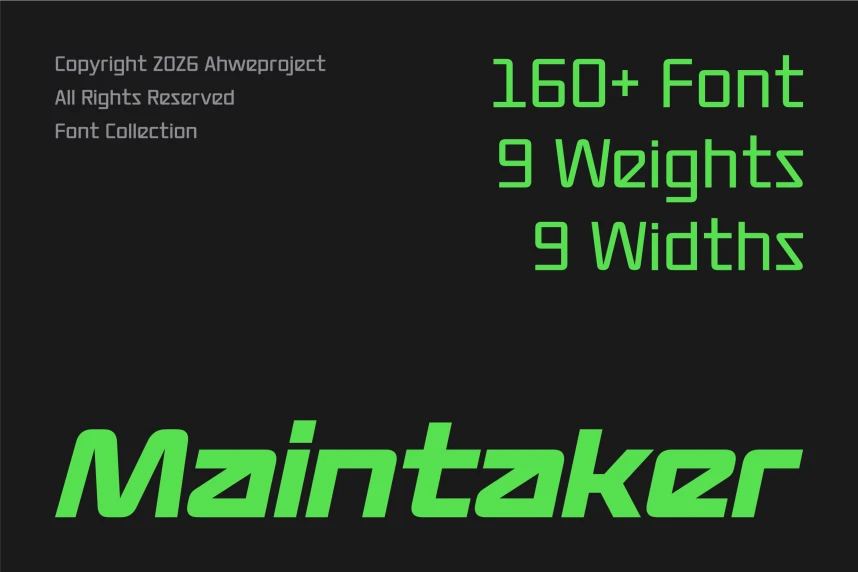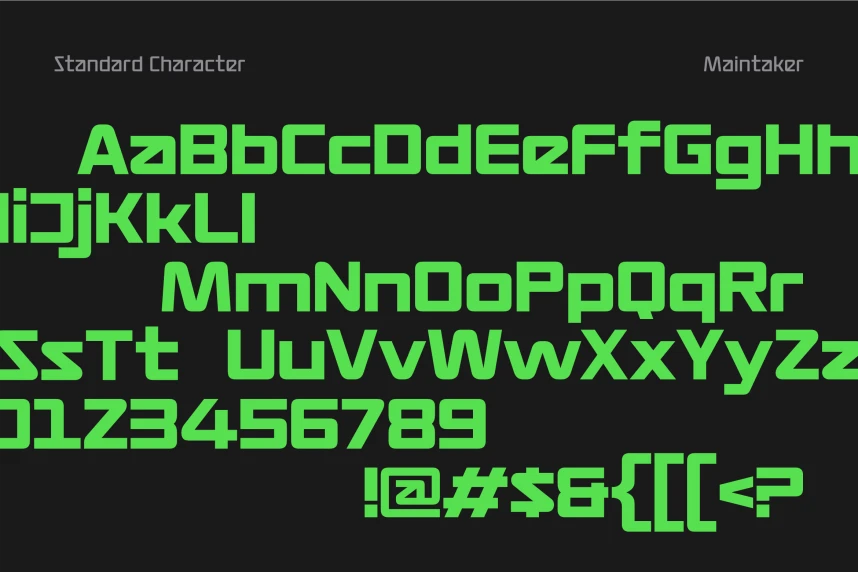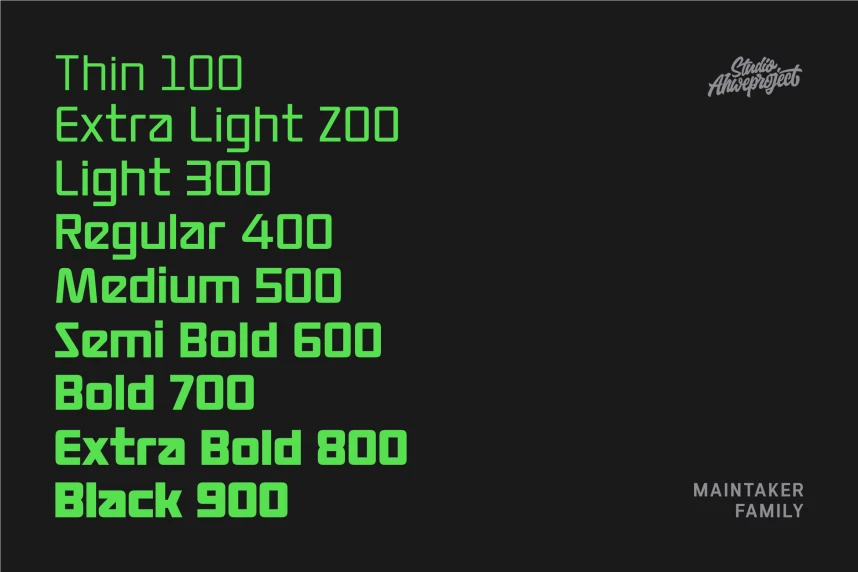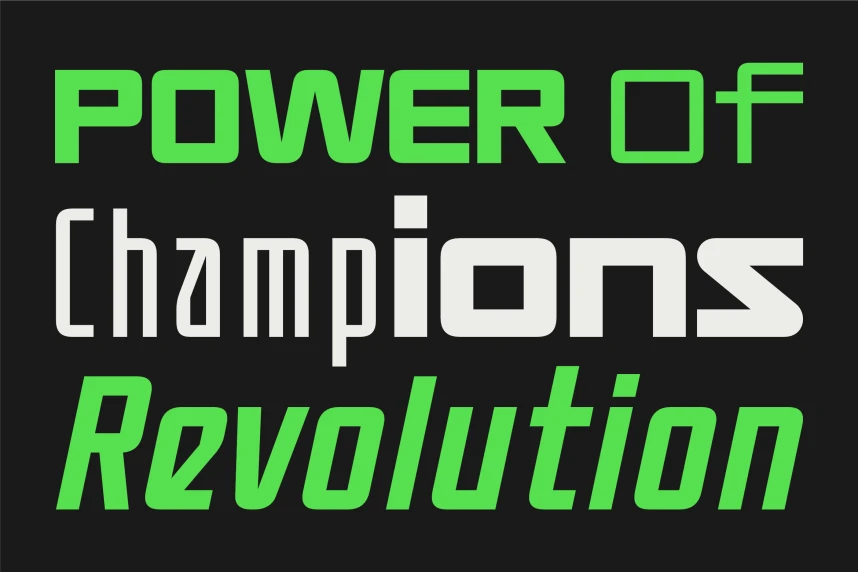
Maintaker Font
Maintaker Font, cesur, modern ve yüksek etkiye sahip görseller isteyen yaratıcılar için tasarlanmış güçlü bir fütüristik font ailesidir. 160'tan fazla stile sahip, 9 ağırlık ve 9 genişlik dahil. Maintaker, sade minimalist düzenlerden agresif, teknoloji ilhamlı marka kimliğine kadar her şeyi tasarlam
Maintaker Font, cesur, modern ve yüksek etkiye sahip görseller isteyen yaratıcılar için tasarlanmış güçlü bir fütüristik font ailesidir. 160'tan fazla stile sahip olan ve 9 ağırlık ile 9 genişlik içeren Maintaker, zarif minimalist düzenlerden agresif, teknoloji ilhamlı markalaşmaya kadar her şeyi yaratmanız için size tam kontrol sağlar.